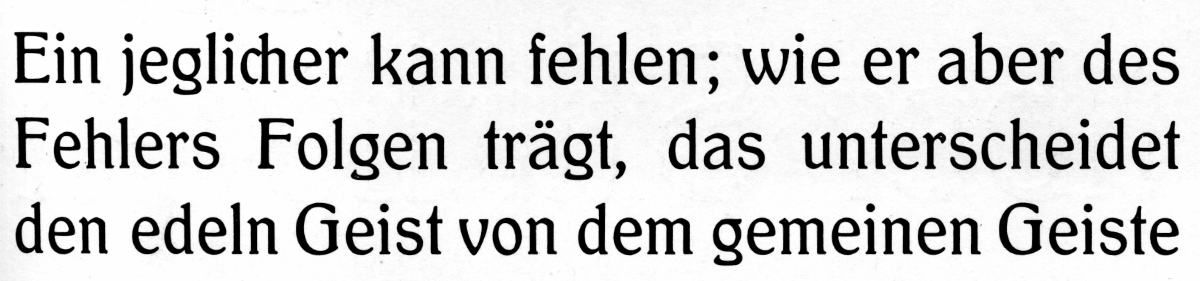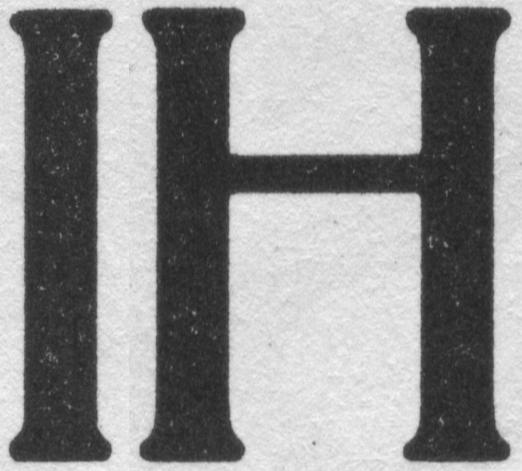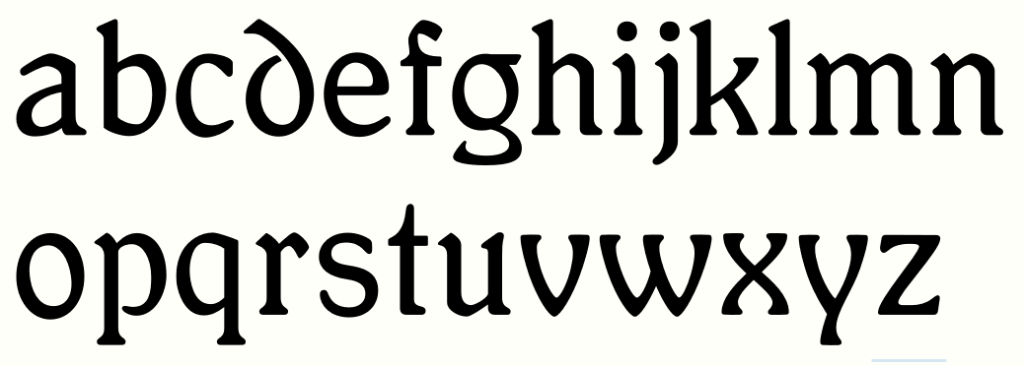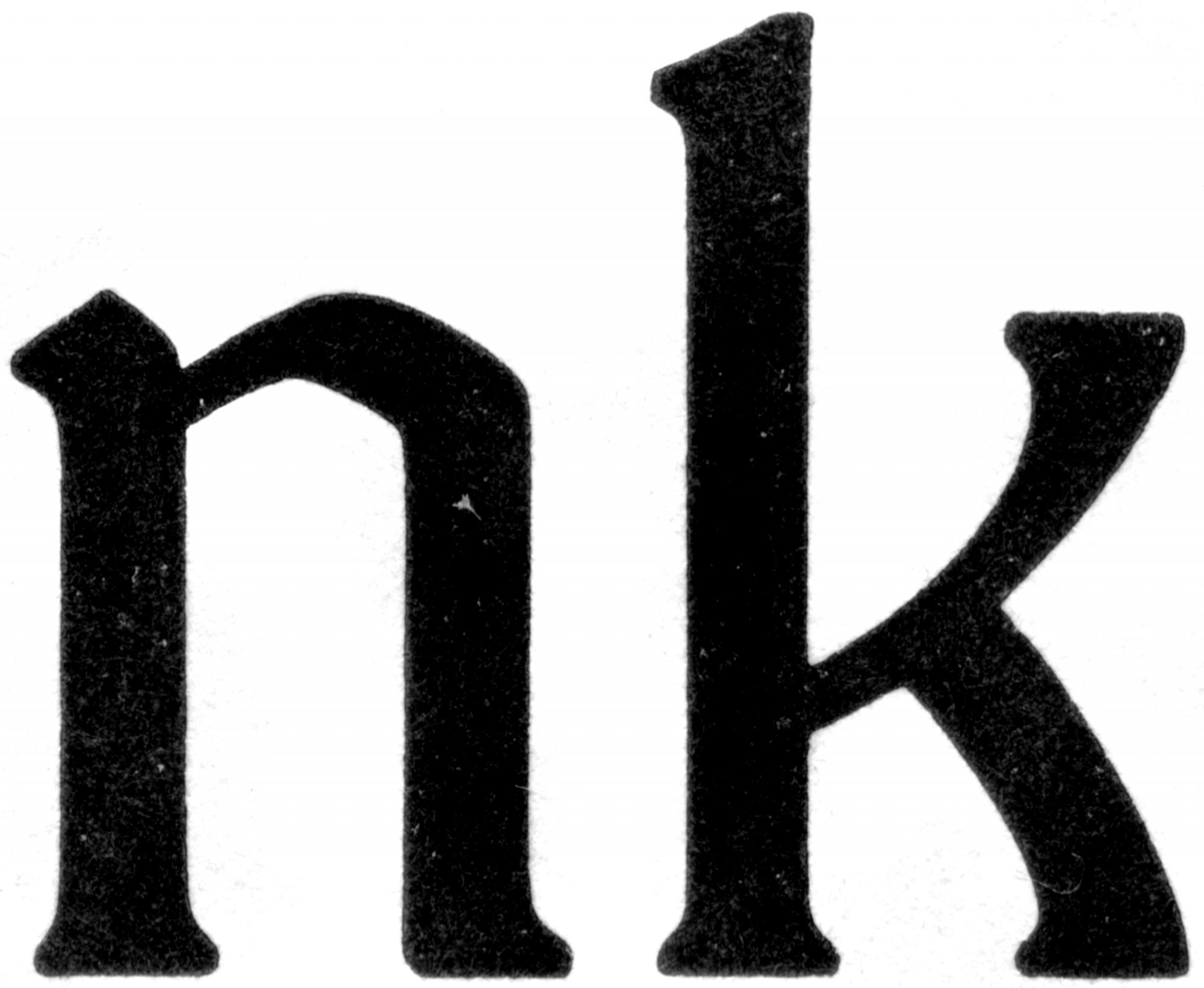
Jugendstil, die Letzte: Schelter Antiqua
Die "show boats" sind alle zu Wasser gelassen; es fehlt nur noch eine zeitgerechte Brotschrift. Dazu habe ich mir die Schelter Antiqua ausgesucht, weil sie etwas blumig, trotzdem erhaben, und sehr gut zu lesen ist. Wer die Schrift entworfen hat, ist mir nicht bekannt. Sie wurde 1905 von Schelter & Giesecke in sechs Schnitten herausgebracht, und war noch in einer Probe von 1932 enthalten. fontsinuse.com stellt eine Ähnlichkeit mit ITC Souvenir fest.
Ich mache erst mal nur einen Schnitt in aufrecht (wie nennt man "regular" auf deutsch?) und kursiv (also eigentlich zwei Fonts). Das ist übrigens noch nicht das Ende vom Lied – es kommt noch ein Font mit Schmuck und Einfassungen dazu, um das Design Kit abzurunden.
Hier mal eine dumme Frage: Bei manchen Schriften sind die linken und rechten Serifen ungleich, und zwar nicht nur bei K, R, usw. wo das dem Kontrast dienlich ist, sondern auch beim I. Ich erkenne da kein System. Ist das gewollt? Oder nur ein Resultat des Andrucks/Tintenflusses?
Im folgenden Beispiel (~36 pt) haben die linken Serifen beim I einen sanfteren Anstieg, und sehen kräftiger aus, die rechten haben eine schärfere Kurve und wirken darum kleiner. Beim H ist das aber andersherum?
Gibt es da irgendwelche Regeln, die ich befolgen sollte?
Ich hab keine Ahnung von den asymmetrischen Serifen, aber einen Scan der 60 pt Schriftprobe.
Wenn es Dir hilft, kann ich auch die ganze Zeile mailen. Die niedrigaufgelöste Seite ist auf meiner Flickr-Seite im Album Schelter & Giesecke zu finden.
Vielen Dank für das Angebot! Ich mache allerdings einen kleineren Schnitt der Schrift. Was ich dazu wirklich brauchen könnte, wäre ein vernünftiger scan (oder Photo) hiervon:
keine Regel
Das scheint auch die Meinung bei typedrawers.com zu sein, wo ich dieselbe Frage stellte. Ich mache mal zuerst alles symmetrisch, und feile dran rum bis es stimmt.
Zu diesem Zeitpunkt waren die Stempeln bei Schelter & Giesecke  – zumindest zum Teil – mit der Hilfe von Pantografen geschnitten. Unter Umständen entstand das Design dieser Schrift also zuerst als Zeichnung auf Papier. Worauf ich hinauf will: Ich sähe es skeptisch, dass die asymmetrische Serifen »einfach so« von den Stempelschneidern hineingebracht wären. Zumindest bei dieser Schrift bzw. bei dieser Firma zu dieser Zeit. Ich kann dir leider nicht sagen, wieso asymmetrische Serifen Teil des Designs waren, aber die Entscheidung dafür war wahrscheinlich bewusst.
Die Stempel wurden tatsächlich mit Pantographenfräsen geschnitten? Kann ich mir zwar kaum vorstellen, dass man damit so etwas hinbekommt bei Brotschrift oder noch kleiner, aber klingt interessant. Bis welche Grade/Größen (abwärts) hat man das gemacht?
Die Benton’sche Stempelschneidemaschine würde in den 1880er-Jahren in den USA erstmals verwendet und relativ schnell bei der Mergenthaler Linotype Company sowie bei der American Type Founders Company auch für sehr kleine Grade verwendet. In Deutschland kann es sein, dass diese Maschine ausschließlich oder zumindest überwiegend bei der D. Stempel AG für den Schneiden der Stempeln verwendet, die dann in der Produktion der Linotype-Matrizen die Matrizen eben schlugen. Stempel hat wohl diese Pantographen wie Mergenthaler Linotype auch für kleine Grade eingesetzt. Es hat auch ein bisschen erst gedauert, bevor Linotype-Maschinen überhaupt so erweitert wurden, dass sie größere Graden setzen könnten. Mengensatz war immer ihrer Haupteinsatzgebiet. Selbst wenn Stempel diese Pantographen nie für die Erstellung von Stempeln für Handsatzschriften eingesetzt hätte, gibt es doch die Beispiele aus ATF, bzw. aus Bentons früheren Schriftgießerei.
Schon in den frühen 1890er-Jahren erwähnte Schelter & Giesecke, dass sie Pantographen in der Stempelherstellung eingesetzt hatten, nicht für das Schneiden von den Stempeln, aber für das Übertragen von den Zeichen ihren Umrisse. Zu dem Zeitpunkt waren die Stempeln noch danach per Handschnitt gefertigt. Schelter & Giesecke war was man ein »early adopter« von amerikanischen Entwicklungen im Schriftgießereiwesen, also kann ich es mir vorstellen, dass sie Pantographen auch beim Stempelschnitt ausprobiert haben. Im Laufe des 20. Jahrhunderts haben die Schriftgießereien immer öfters die Matrizen ihren Schriften mit Pantographen gebohrt, ganz ohne Stempeln also. Auch in sehr kleine Graden machten sie das. Die genaue Zeitpunkt dieser Einführung war von Firma zu Firma stark unterschiedlich. Gursch setzte schon um 1900 darauf, Berthold erst 1910 und Stempel (für den Handsatz) wahrscheinlich etwas später aber auf allen Fällen bis den frühen 1920er Jahren. Gebr. Klingspor dagegen setzte Matrizenbohrmaschinen kaum ein.
Wenn Pantographen nicht verwendet waren, wurde es schon etwa in den 1880er oder 1890er Jahren standard, dass die Grade ab etwa 28pt im Zeugschnitt erstellt würden sind (womit Matrizen über galvanoplastische Methoden anschließend hergestellt waren), darunter im Stahlschnitt. Wobei einige Gießereien verwendete nur bis etwa 12pt den Stahlschnitt. Auch kommt dazu, dass mehr und mehr Gießereien den Zeugschnitt mit Pantograph-Maschinen machten. Pantograph-Maschinen waren in der Bedienung schneller als die reine Handarbeit und man könnte (und hatte) Arbeiter daran gesetzt, die keine Stempelschnitt- oder Graveurausbildung durchlaufen sind. Die Stempelschneider waren eher gegen der Einführung dieser Maschinen, aber als Sparte innerhalb der Gewerbe haben sie eher wenig Macht gehabt (anders die Schriftgießer, die an den Gießmaschinen standen), selbst wenn Stempelschneider in jüngster Zeit in der Grafikdesign-Branche heroisiert worden sind.
Das wichtigste aus der Arbeit mit Pantografen (ob für den Stempelschnitt oder die Übertragung von Umrisse): Dafür muss es schon Master-Zeichnungen gegeben haben. Die Schriften von Schelter & Giesecke zu dieser Zeit waren zuerst von Zeichnern auf Papier entworfen, bevor sie in der Produktion gingen. Das ist ein starker Bruch gewesen: So haben Stempelschneider wie Johann Christian Bauer oder seinen Sohn Friedrich Wilhelm Bauer vermutlich nicht gearbeitet. Das Design ihrer Schriften war untern Umständen etwas flüssiger und sie entschieden über bestimmte Details noch beim Schnitt. Wenn das Design aber vorgegeben war, dann wären Details wie die asymmetrische Serifen der Schelter Antiqua schon da, bevor sie geschnitten wurde, und somit keine »Produktionsfehlern« sondern (höchstens) Nachteilen am Design. Ich persönlich bin eher Fan von asymmetrischen Serifen und finde sie in diesem Fall nicht schlecht. Unter Umständen können sie bestimmt das gesamte Schriftbilder »warmer« machen.
Das H finde ich, ähnlich dem T, auch noch etwas zu stark. Aber vielleicht ist das ein generelles »Feature« der Senkrechten in den Großbuchstaben … Den Bug beim A hast du bestimmt selbst schon bemerkt, oder?1842278777_Bildschirmfoto2020-09-16um19_13_56.png.646162d176718bd498c39f1da9a9196d.png
Einen schönen guten Morgen wünsche ich. Gestern Abend zog ich ein paar schicke Nummern durch, und zwar diese:
Die Neun ist links etwas dünnwandig. Fällt Euch sonst noch was auf?